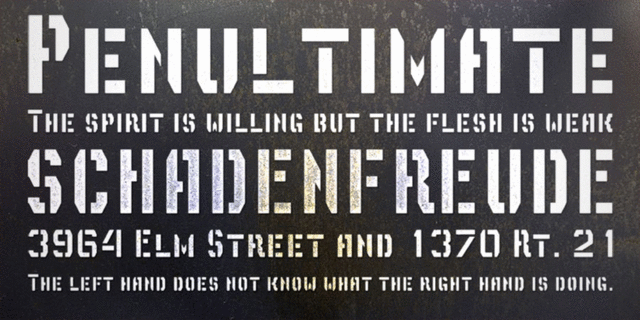
Шрифт Депо Трафарет 2D сделан по мотивам надписей на стендах трамвайных маршрутов Львова. Шрифт отличается брутальностью и простотой, граничащей с примитивизмом. Разработан Лукьяном Турецким в 2006 году.